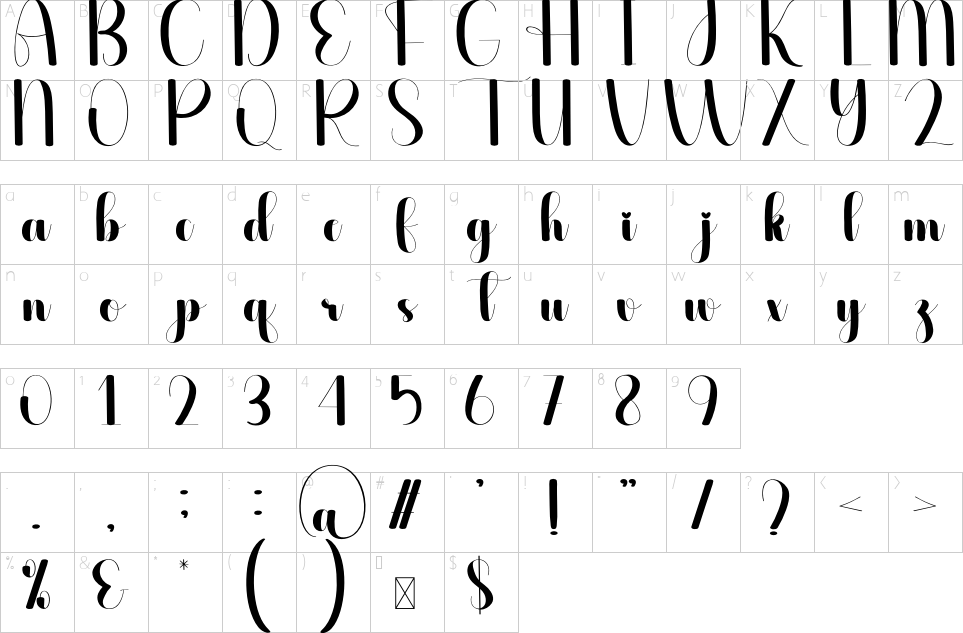
Aurora Font – Download Grátis
Aurora é uma fonte moderna e elegante, perfeitamente adequada para projetos gráficos variados. Ela foi projetada por um designer não identificado e já foi baixada 330 vezes. Com um design minimalista, Aurora destaca-se por sua levedade e facilidade de uso. Suas linhas finas e equilibradas garantem um resultado limpo e moderno em qualquer aplicação de design. Seja para o seu website, aplicativo de mobile ou design de material impresso, Aurora está equipada para oferecer a elegância e a simplicidade que você precisa. Seja sua escolha para criar um design atraente, é uma fonte que merece uma oportunidade.